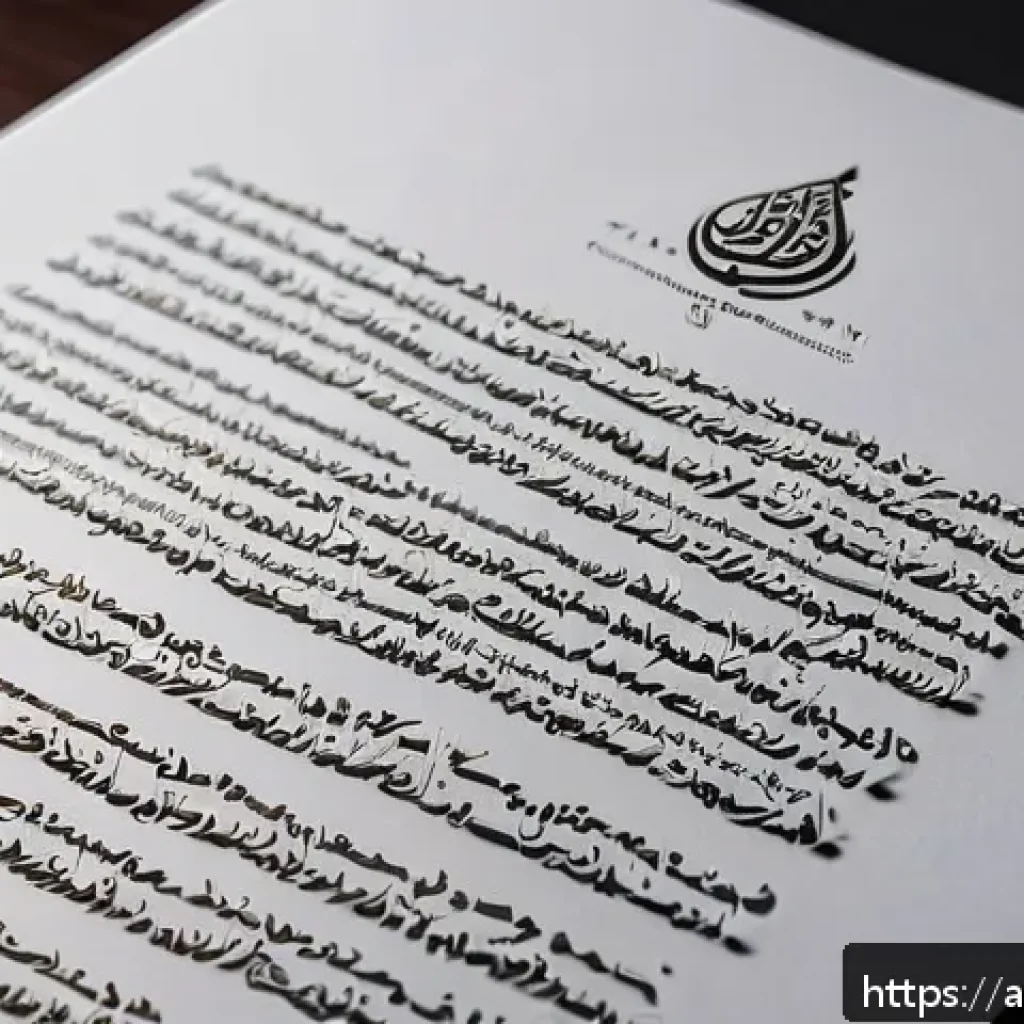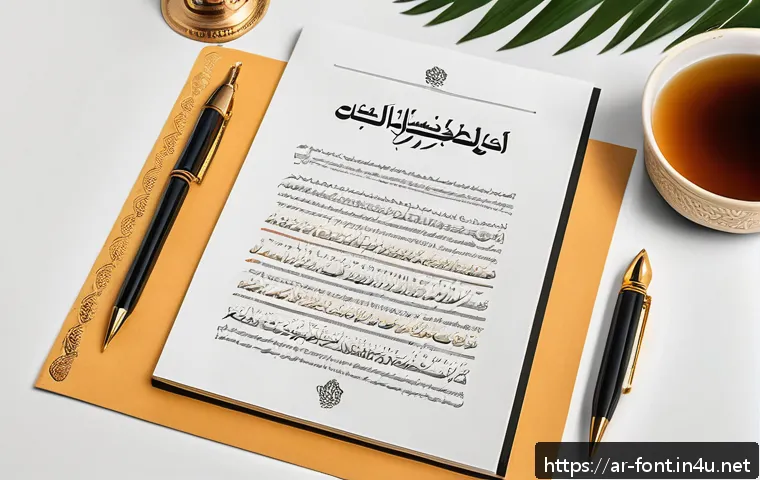
كيف تضبط نسب الخط وحجمه لتحصل على مستندات مثالية وجذابة؟
في عالمنا الرقمي المتسارع، أصبحت جودة المستندات وتأثيرها البصري من أهم عوامل جذب القارئ والحفاظ على انتباهه. مع تزايد استخدام المستندات الإلكترونية في مختلف المجالات، أصبح ضبط نسب الخط وحجمه فنًا لا غنى عنه لتحقيق تصميم متوازن وجذاب.
مؤخرًا، شهدنا توجهًا واضحًا نحو تبني أنماط كتابة تركز على الوضوح والراحة البصرية، مما يجعل فهم النصوص أسهل ويقلل من معدل التخلي عنها. في هذا المقال، سأشارككم تجاربي الشخصية وأفضل النصائح التي تساعدكم على ضبط الخطوط بشكل مثالي، لتخرج مستنداتكم بمظهر احترافي يجذب الجميع ويزيد من فعالية المحتوى.
تابعوا معي لتتعرفوا على أسرار تصميم نصوص لا تُقاوم!
اختيار الخط المناسب وتأثيره على تجربة القارئ
كيف يحدد نوع الخط وضوح المحتوى؟
عندما تبدأ في تصميم مستند، لا يمكن الاستخفاف بأهمية اختيار نوع الخط المناسب. الخطوط مثل “Arial” أو “Tahoma” تقدم وضوحًا عاليًا وسهولة في القراءة، بينما الخطوط المزخرفة قد تبدو جذابة لكنها تصعب عملية القراءة، خصوصًا في المستندات الطويلة.
من تجربتي الشخصية، استخدمت خطوطًا بسيطة في التقارير الرسمية ولاحظت تحسنًا واضحًا في تفاعل القارئ مع النص، حيث قلّت نسبة التخلي عن القراءة بشكل ملحوظ. لذلك، أنصح دائمًا بأن يكون الخط واضحًا وخاليًا من التعقيدات، خصوصًا عند توجيه المحتوى لجمهور عام.
تأثير حجم الخط على راحة العين
حجم الخط له دور كبير في راحة العين أثناء القراءة. حجم صغير جدًا يجعل القارئ يشعر بالإرهاق، وحجم كبير جدًا قد يشتت الانتباه ويُظهر النص بشكل غير منسجم.
بناءً على تجاربي، الحجم المثالي للنص الأساسي يتراوح بين 12 إلى 14 نقطة، أما للعناوين فيفضل أن تكون أكبر قليلًا لتسليط الضوء عليها. في بعض الأحيان، جربت استخدام حجم 11 في مستندات تحتوي على معلومات كثيفة، ولاحظت تراجعًا في التركيز وسرعة القراءة.
التوازن بين الخط والمسافات
لا يكفي ضبط حجم ونوع الخط فقط، بل يجب مراعاة التباعد بين الحروف والأسطر. التباعد المناسب يجعل النص يبدو متنفسًا ويسهل متابعته. قد جربت عدة مرات ضبط التباعد يدويًا، ووجدت أن زيادة التباعد بين الأسطر بنسبة 1.5 تعطي مظهرًا أكثر احترافية وتريح العين، على العكس من التباعد الضيق الذي يجعل الصفحة مكتظة وغير مريحة.
تنسيق النصوص لتعزيز الجاذبية البصرية
استخدام الألوان بحكمة في النصوص
الألوان ليست فقط لجذب الانتباه، بل أيضًا لتحسين فهم القارئ للنص. قمت بتجربة استخدام ألوان خفيفة مثل الرمادي الداكن للعناوين والرمادي الفاتح للنصوص الثانوية، ووجدت أن هذا التدرج يقلل من إجهاد العين أثناء القراءة الطويلة.
كما أن الألوان الزاهية يمكن أن تشتت القارئ إذا استخدمت بشكل مفرط، لذلك يجب وضعها بعناية وفي أماكن استراتيجية مثل العناوين أو النقاط المهمة.
تطبيق التنسيق المتناسق عبر المستند
التناسق في الخطوط والألوان والهوامش يجعل المستند أكثر احترافية. من خلال تجربتي، لاحظت أن المستندات التي تحتوي على تنسيق غير متناسق تفقد مصداقيتها بسرعة، حتى لو كان المحتوى جيدًا.
لذلك، من الأفضل إعداد قالب موحد قبل البدء في كتابة المستند لضمان الاتساق في جميع الصفحات.
دور التنسيق في تحسين قابلية الطباعة
أحيانًا قد يبدو المستند جميلًا على الشاشة لكنه يخرج بشكل مختلف عند الطباعة. جربت طباعة نسخ من مستنداتي بعد التنسيق وتعديل الألوان والخطوط لأتأكد من وضوحها على الورق.
اكتشفت أن الخطوط الداكنة مع خلفية بيضاء توفر أفضل وضوح، كما أن الحفاظ على هوامش مناسبة يمنع قطع النص أثناء الطباعة.
الهيكلية الذكية للمستندات وتأثيرها على القراءة
تقسيم المحتوى إلى فقرات واضحة
تقسيم النص إلى فقرات قصيرة ومنظمة يزيد من قابلية القراءة ويجعل القارئ لا يشعر بالملل. بناءً على تجربتي، أحاول ألا تتجاوز كل فقرة 5 إلى 7 أسطر، مع ترك مسافة واضحة بين الفقرات.
هذا الأسلوب يُعطي إحساسًا بالتنفس ويشجع القارئ على متابعة القراءة بدون إرهاق.
استخدام العناوين الفرعية بشكل استراتيجي
العناوين الفرعية تُساعد القارئ في فهم محتوى المستند بسرعة وتحديد النقاط المهمة. جربت استخدام عناوين فرعية واضحة ومختصرة، مع تنسيق مختلف (مثل حجم أكبر أو لون مختلف) لتسليط الضوء عليها، وكان لذلك تأثير إيجابي في تحسين تجربة القراءة.
بالإضافة إلى ذلك، العناوين تساعد في تحسين ترتيب المستند في محركات البحث.
تعزيز التفاعل عبر إدراج نقاط وقوائم
القوائم النقطية أو الرقمية تجعل المحتوى أسهل في الفهم والهضم، خصوصًا عند سرد الخطوات أو النقاط المهمة. في مستنداتي، أستخدم القوائم بشكل متكرر وألاحظ أن القارئ يميل للبقاء لفترة أطول عند وجود هذه القوائم لأنها تسهل استيعاب المعلومات بسرعة.
تجربة المستخدم وتأثير الخطوط على الانطباع الأول
أهمية الخطوط في بناء هوية المستند
الخطوط ليست مجرد حروف، بل هي جزء من الهوية البصرية للمستند. عندما أستخدم خطًا معينًا يتناسب مع موضوع المستند، أشعر أن القارئ يتفاعل بشكل أفضل ويُكوّن انطباعًا إيجابيًا منذ اللحظة الأولى.
مثلاً، الخطوط الرسمية تعطي شعورًا بالجدية، أما الخطوط الحديثة فتضفي لمسة عصرية.
كيف تؤثر الخطوط على سرعة القراءة؟
من خلال مراقبتي لقراءة المستندات، لاحظت أن الخطوط السلسة والواضحة تساعد القارئ على الانسيابية في القراءة دون توقف أو تردد. أما الخطوط المزخرفة أو الضيقة فتبطئ من سرعة القراءة وتجعل القارئ يشعر بالإرهاق، مما يدفعه غالبًا لترك المستند قبل إكماله.
تجربة شخصية مع تعديل الخطوط
ذات مرة قمت بتعديل خط تقرير رسمي من “Times New Roman” إلى “Calibri”، ولاحظت تغيرًا كبيرًا في تعليقات الزملاء الذين وجدوا التقرير أسهل وأسرع قراءة. هذا الأمر جعلني أحرص على اختبار الخطوط المختلفة قبل اعتمادها، لأن التأثير على القارئ قد يكون أكثر من مجرد مسألة جمالية.
Advertisement
أدوات وتقنيات لضبط الخطوط بشكل احترافي
استخدام برامج تحرير النصوص المتقدمة
برامج مثل Microsoft Word وAdobe InDesign توفر أدوات دقيقة لضبط حجم الخط، التباعد، والمحاذاة. بعد تجربة عدة برامج، وجدت أن InDesign يقدم خيارات أكثر مرونة خاصة للمستندات المعقدة، حيث يمكنني التحكم في كل تفصيلة صغيرة للحصول على تصميم مثالي.
تجربة الخطوط عبر مختلف الأجهزة
أحيانًا يظهر الخط بشكل مختلف على شاشات الكمبيوتر، الهاتف، أو الطابعة. لذلك، أحرص على معاينة المستند على أكثر من جهاز قبل الاعتماد النهائي. هذا يساعدني على التأكد من أن الخطوط والحجوم متناسقة ومريحة لجميع القراء، بغض النظر عن الجهاز المستخدم.
جدول مقارنة بين خصائص الخطوط الشهيرة
الخط وضوح القراءة الاستخدام الأمثل التباعد الموصى به
Arial عالي جدًا المستندات الرسمية والويب 1.15 – 1.5
Times New Roman جيد الكتب والتقارير التقليدية 1.0 – 1.15
Calibri عالي العروض التقديمية والمراسلات 1.15 – 1.5
Tahoma عالي جدًا النصوص القصيرة والعناوين 1.2 – 1.5
Advertisement
نصائح متقدمة لضمان جودة الطباعة والعرض الرقمي
ضبط الخطوط للطباعة بجودة عالية
تجربتي مع الطباعة علمتني أن الخطوط الداكنة ذات الحواف الواضحة تعطي أفضل نتائج على الورق. من المهم أيضًا اختيار حجم خط لا يقل عن 10 نقاط عند الطباعة لتجنب ضياع التفاصيل.
بالإضافة إلى ذلك، يجب الانتباه إلى نوع الورق المستخدم، حيث يؤثر بشكل كبير على وضوح الخط.
تحسين الخطوط للعرض على الشاشات المختلفة
في العصر الرقمي، كثير من المستندات تُقرأ على شاشات مختلفة الأحجام. لذلك، من الضروري اختيار خطوط تتكيف مع شاشات الهواتف، الحواسيب، والأجهزة اللوحية. من خلال تجربتي، الخطوط ذات التصميم البسيط والسلس مثل “Verdana” تظهر بشكل أفضل على الشاشات الصغيرة.
تجنب الأخطاء الشائعة في ضبط الخطوط
أكثر الأخطاء التي رأيتها هي استخدام خطوط كثيرة في مستند واحد أو تغيير حجم الخط بشكل مبالغ فيه. هذه الممارسات تشتت القارئ وتفقد المستند هيبته. أنصح دائمًا بتحديد خطين كحد أقصى مع التزام بحجم ثابت للنص الأساسي، مع تغيير حجم الخط فقط للعناوين أو النقاط المهمة.
Advertisement
خاتمة المقال
اختيار الخط المناسب ليس مجرد مسألة جمالية، بل هو عامل أساسي يؤثر على تجربة القارئ ووضوح المحتوى. من خلال تجربتي، وجدت أن الانتباه لتفاصيل مثل نوع الخط، حجمه، وتنسيقه يجعل المستند أكثر جاذبية ويسهل استيعابه. لذلك، أنصح دائمًا بتجربة الخطوط المختلفة والتأكد من تناسقها مع طبيعة المحتوى والجمهور المستهدف.
Advertisement
معلومات مفيدة يجب معرفتها
1. الخطوط البسيطة والواضحة تعزز من سرعة القراءة وتقليل إرهاق العين.
2. التباعد بين الأسطر والحروف يؤثر بشكل كبير على راحة القارئ أثناء التصفح.
3. استخدام الألوان بحذر يساعد في إبراز النقاط المهمة دون تشتيت الانتباه.
4. معاينة المستند على أجهزة مختلفة تضمن تجربة متناسقة لجميع المستخدمين.
5. الحد من عدد الخطوط المستخدمة في المستند يحافظ على مظهره الاحترافي ويزيد من مصداقيته.
Advertisement
نقاط هامة يجب تذكرها
الخطوط ليست مجرد أدوات لعرض النص، بل هي جزء من هوية المستند وتجربة المستخدم. اختيار الخط المناسب، حجمه، وتنسيقه بشكل متوازن يعزز من وضوح المحتوى ويساعد في إيصال الرسالة بشكل فعال. كما أن التناسق في التنسيق والألوان يلعب دورًا مهمًا في جعل المستند أكثر جاذبية واحترافية.
الأسئلة الشائعة (FAQ) 📖
س: كيف أختار حجم الخط المناسب لمستندي لكي يكون واضحًا وسهل القراءة؟
ج: اختيار حجم الخط المناسب يعتمد بشكل كبير على نوع المستند والجمهور المستهدف. من تجربتي الشخصية، أفضل استخدام حجم خط يتراوح بين 12 إلى 14 للنصوص العادية، لأنه يوازن بين الوضوح والراحة البصرية.
إذا كان المستند يحتوي على عناوين أو فقرات قصيرة، يمكن زيادة حجم الخط قليلاً لجذب الانتباه، أما النصوص الطويلة فحجم الخط الأصغر قليلاً يكون أفضل لتقليل إجهاد العين.
المهم أن تتجنب الخطوط الصغيرة جدًا التي تجعل القراءة متعبة أو الكبيرة جدًا التي تشوش التصميم العام.
س: هل هناك قواعد محددة لنسب الخط بين العناوين والنص الأساسي لضمان توازن التصميم؟
ج: نعم، هناك قواعد بسيطة لكنها فعالة لضبط نسب الخط بين العناوين والنص الأساسي. عادةً ما يكون حجم العنوان الرئيسي أكبر بحوالي 1.5 إلى 2 مرة من حجم النص الأساسي، والعناوين الفرعية يمكن أن تكون أكبر بنسبة 1.2 إلى 1.5.
من خلال تجربتي، هذا التدرج في الحجم يخلق تباينًا بصريًا يساعد القارئ على التمييز بين أجزاء المستند بسهولة، ويمنح المستند مظهرًا أنيقًا ومنسقًا دون أن يشعر بالإرباك أو التشويش.
س: كيف يمكنني تحسين راحة العين عند قراءة المستندات الإلكترونية من خلال ضبط الخط؟
ج: لتحسين راحة العين، يجب الانتباه إلى عدة عوامل متعلقة بالخط، مثل نوع الخط، حجمه، وتباعد الأسطر. أفضل الخطوط التي استخدمتها والتي أعطتني نتائج مريحة هي الخطوط البسيطة والواضحة مثل “Arial” أو “Tahoma”، مع حجم مناسب بين 12 و14.
أيضًا، زيادة تباعد الأسطر قليلاً (حوالي 1.5) يساعد على تقليل الضغط على العين ويجعل النص يبدو أقل ازدحامًا. من تجربتي، الإضاءة المحيطة والتباين بين لون الخط وخلفية الصفحة لهما تأثير كبير، لذا اختر ألوانًا مريحة للعين مثل الأسود على خلفية بيضاء أو رمادية فاتحة.
هذه العوامل مجتمعة تجعل القراءة لفترات طويلة أكثر متعة وأقل إجهادًا.